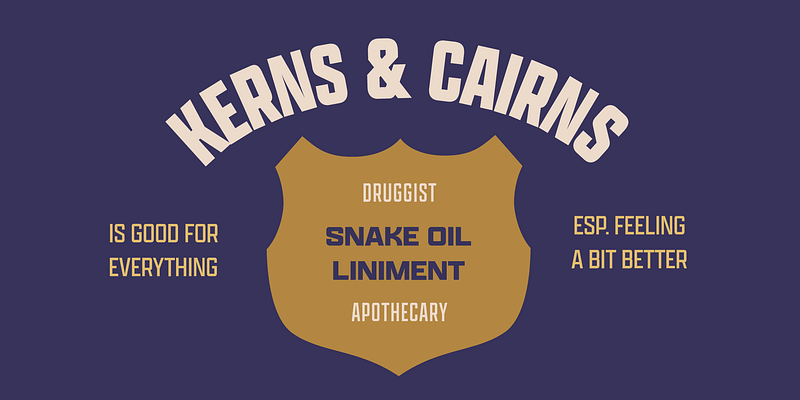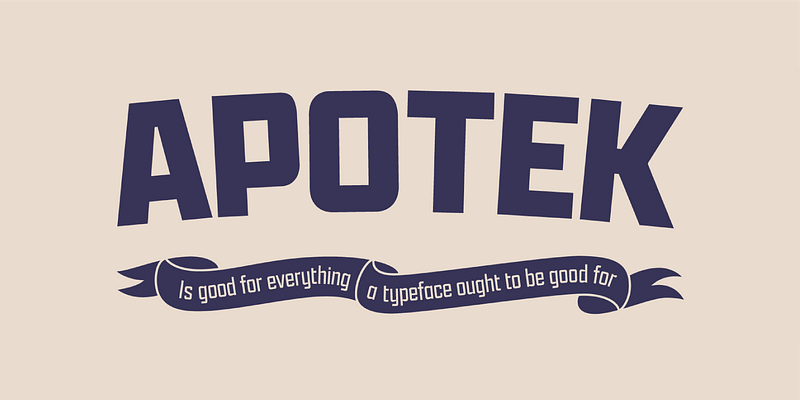
Dyana Weissman n’est généralement pas adepte des polices sans serif, mais lors d’un voyage en Norvège, elle a est tombée sous le charme en voyant les étiquettes de vieux flacons de médicaments exposés dans un musée. Avec leur impact fort, les caractères de ces étiquettes ont inspiré Weissman et l’ont convaincue de faire un essai avec une police sans serif. Partant de sources essentiellement en capitales et dans un seul style, elle a étendu l’idée à une plus grande gamme de graisses et de largeurs. Kerns & Cairns, 2020.